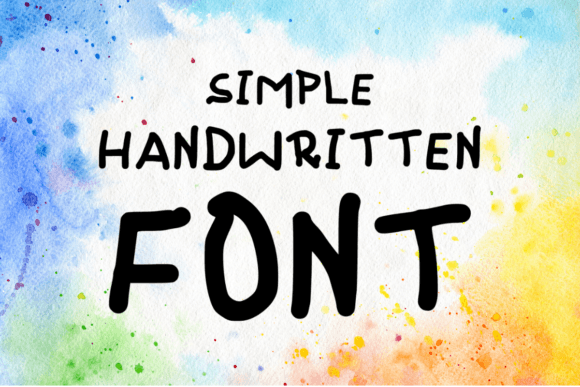
Simple Handwritten
Simple Handwritten – La police manuscrite qui donne vie à vos projets
Vous cherchez une police qui combine authenticité, chaleur et lisibilité ? La police Simple Handwritten répond parfaitement à ces attentes. Conçue pour évoquer le style d’une écriture à la main, elle est idéale pour les cartes de vœux, les affiches inspirantes, les publications sur les réseaux sociaux ou tout autre support où l’on veut transmettre un message personnel et motivant.
Pourquoi choisir Simple Handwritten ?
- Style ludique et élégant : Des lettres légèrement excentriques qui restent faciles à lire, parfaites pour capter l’attention sans sacrifier la clarté.
- Polyvalence maximale : Utilisable en numérique comme en impression – flyers, invitations, blogs, ebooks, et même packaging.
- Authenticité garantie : Le rendu « fait main » apporte une touche humaine et chaleureuse, idéale pour les projets qui cherchent à toucher le cœur du public.
Comment Simple Handwritten booste votre créativité
En intégrant Simple Handwritten à vos créations, vous obtenez immédiatement une vibration positive qui incite à l’action. Que vous réalisiez un poster motivant (« Croyez en vous ») ou une carte de remerciement personnalisée, cette police apporte une dimension émotionnelle qui rend chaque mot plus impactant.
En résumé, Simple Handwritten est la solution idéale pour quiconque souhaite ajouter une touche personnelle et encourageante à ses créations. Sa lisibilité, son charme ludique et sa facilité d’utilisation en font un incontournable pour les designers, les blogueurs et les entrepreneurs créatifs. Téléchargez la police maintenant et laissez votre inspiration prendre forme avec une écriture qui ressemble à votre propre main.